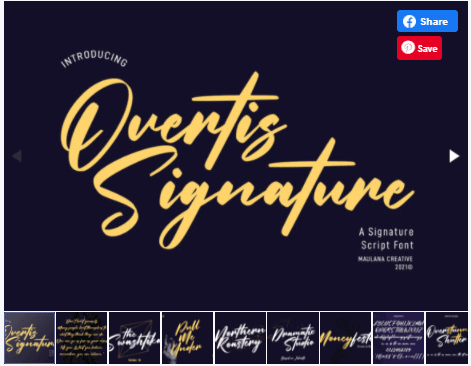
Overtis Signature Font
Overtis Signature - это простой и плавный рукописный шрифт. Этот адаптируемый шрифт отлично подойдет для самых разных дизайнерских идей. Это добавит веселья и дружелюбия каждому из ваших проектов!